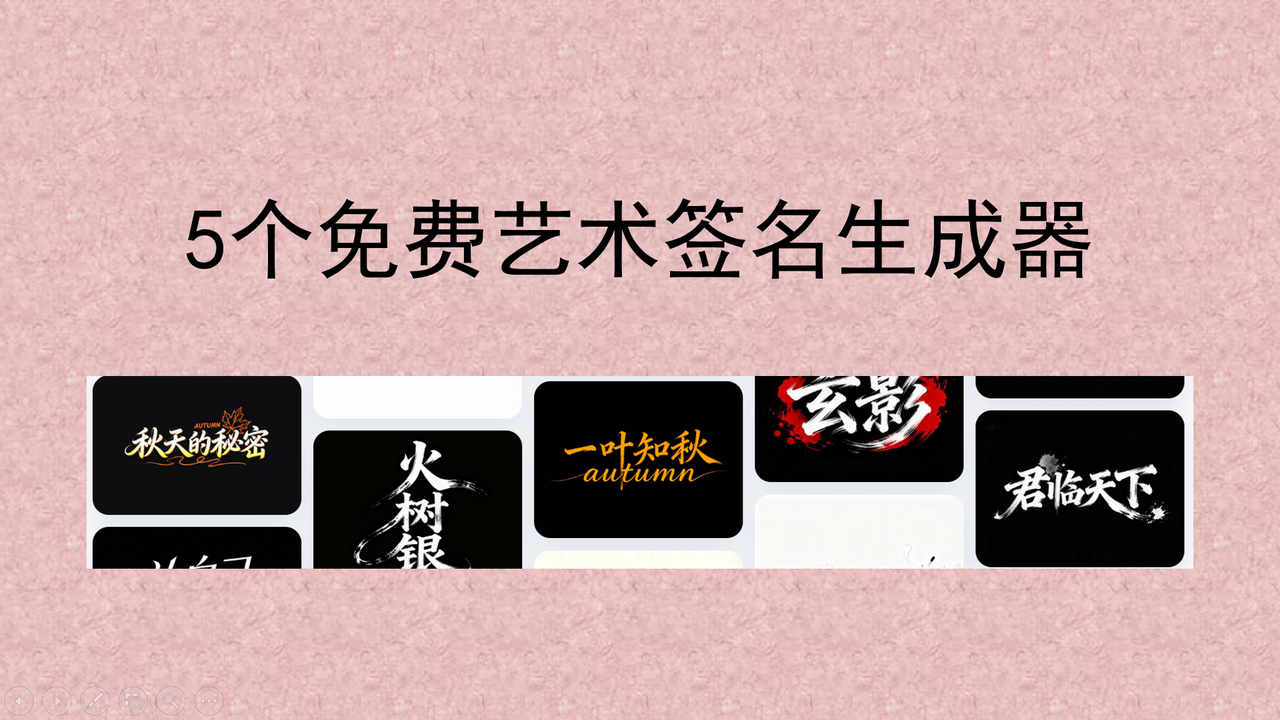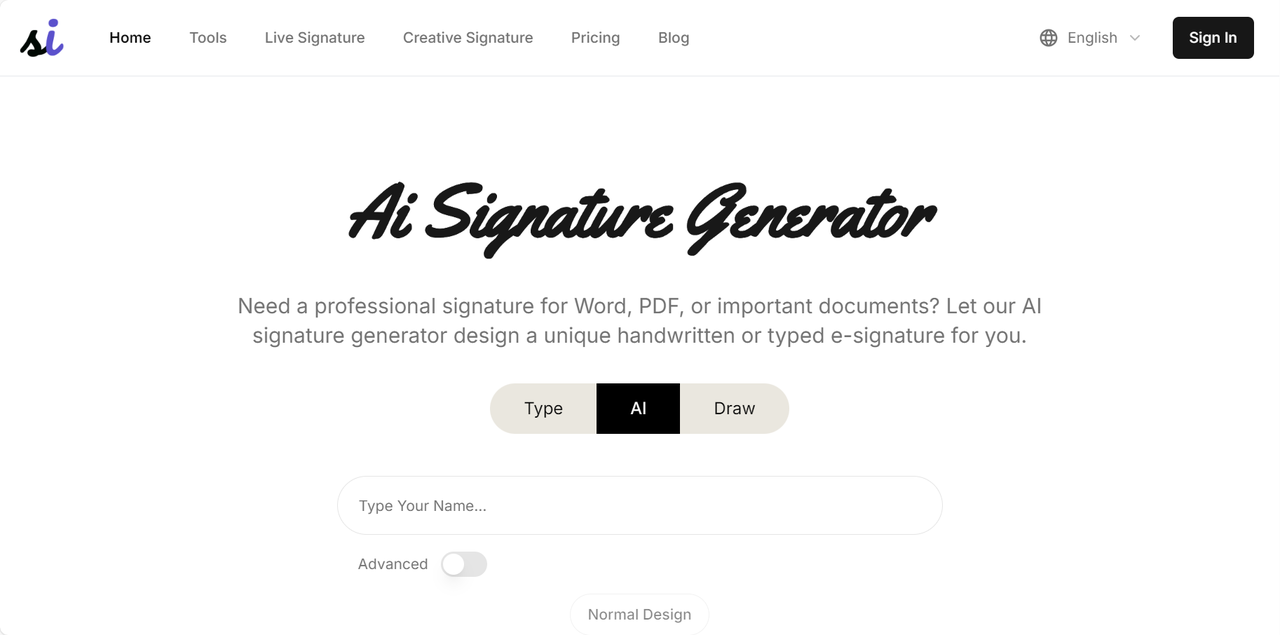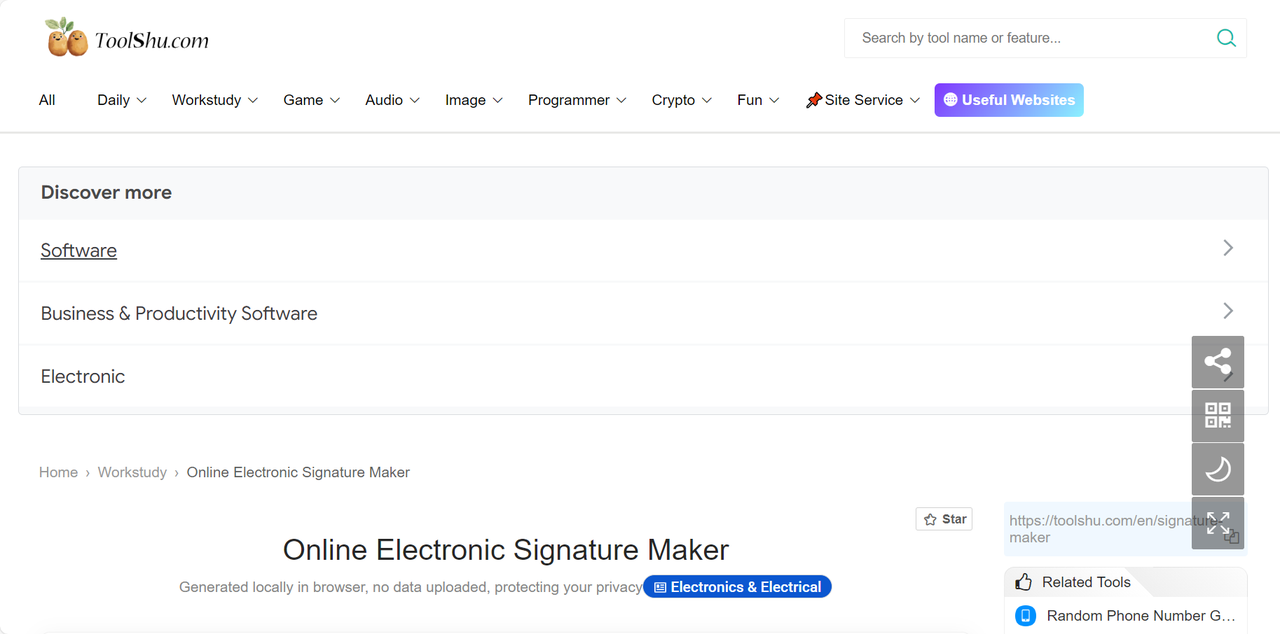
不用找设计师!免费艺术签名在线生成,3 秒出效果
很多人手写签名练的很好,但是一到电子签名时就歪歪扭扭,控制不好鼠标,连自己看了签名都觉得不够体面。一个与众不同的艺术签名,不仅能够彰显个人品位,更是个人品牌形象的重要组成部分。在当今科技飞速发展的时代,大家完全不必再为设计签名而苦恼,很多免费的艺术签名在线生成工具都能快速设计签名,短短几秒就能获得一款高颜值手写风艺术签名!生成后的签名还可以直接保存为透明背景的图片,不管是电子合同、简历、PPT、邮件还是其他场景,都可以直接一键应用。接下来就给大家介绍 5 个亲测好用的艺术签名生成工具,彻底告别“手残党”的尴尬!
一、字由
字由是国内设计师最常用也最方便的一款字体工具,目前已有超过 2000 万用户注册使用,提供500+品质正版字体商用授权,并提供 AI 识字、字体特效等实用设计工具,是设计师必备的字体管理神器。除此之外,在帮助普通人打造艺术签名这个领域,字由也是一个绝佳助手,最简单便捷的方式就是利用它的 AI 字体功能。打开字由官网,在上方菜单栏点击【字体工具】——【AI 字体】,进入后可以看到上百种 AI 模板,包含多种字体风格;我们在分类筛选区域点击“个性签名”,找到自己喜欢的艺术签名效果,在文本框输入你的名字,等待 30s 就可以得到一张同款艺术字签名。输入的文本字数最好和模板样图的字数一致哈,这样字体生成效果会比较准确,也更容易符合你的预期。这里建议大家下载的时候选择透明背景的 PNG 图片格式,这样便于后续直接使用。
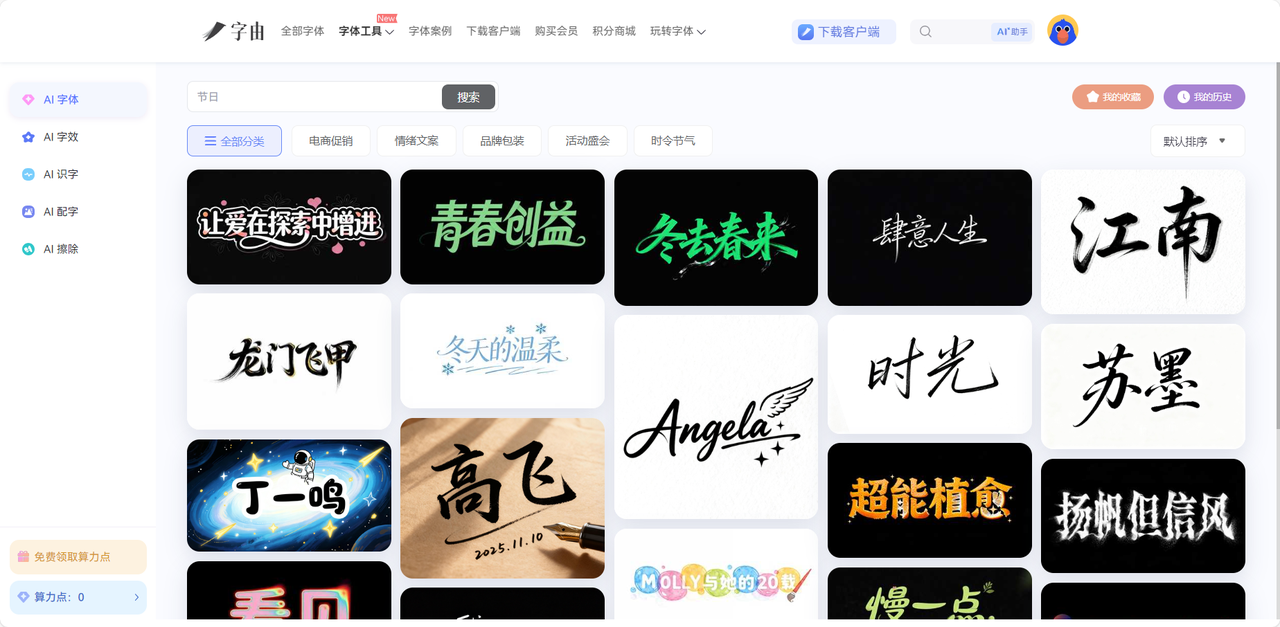
二、SignatureGen.ai
SignatureGen.ai 是一款 AI 驱动的在线签名生成工具,只需要输入你的名字,系统就会自动生成多种风格的艺术字签名供你选择。它提供了三种生成艺术签名的方式:常规字体签名、AI 生成签名和手写模拟签名。我最常用的还是 AI 生成签名,这也是 SignatureGen.ai 最大的特色,你可以额外向它描述想要生成的字体风格倾向,给它提要求,要求越详细越容易生成你满意的签名效果,而且它的笔触还是比较真实的。如果你偏向于更华丽的签名设计,SignatureGen.ai 还有一个创意签名的功能,可以将签名和简单的简笔画元素融合到一起,比如会在某些笔画边缘嵌入一朵小花、一颗星星、一片叶子等极简的图标,可以让你的签名更具辨识度。
三、Toolshu Electronic Signature Maker
对于非常注重隐私和数据安全的用户而言,Toolshu Electronic Signature Maker 堪称最理想的选择,它是一款可以完全在浏览器本地运行的电子签名生成工具,所有操作都是在本地完成的,自己的名字也不会被上传到网络服务器。说起艺术字签名,用户想要体验更高自由度的设计过程可以选择它的手绘模式签名设计,也就是说直接用鼠标、触控板或者手写笔在绘图板上书写签名。它会根据书写速度自动调节线条的粗细变化,模拟真实手写字体的笔墨变化,更加真实自然随性。不过这个功能也比较考验用户自身的书写能力,不适合新手小白哦。觉得自己的手写效果不够好看,还可以选择 Toolshu Electronic Signature Maker 字体生成模式。你只需要挑选一款自己满意的书法字体风格,输入自己的姓名,点击生成就可以获得同款字体的签名了。
四、Refont AI
提起 Refont AI,大家应该也比较熟悉了,它是一款兼具艺术性与个性化的手写签名生成工具,输入姓名后,可以快速将其转化为手写体或是各种书法风格的签名。Refont AI 最大的特色在于它对书法美学 的专注研究,毫不夸张地说,用它生成的签名都会带有真实的笔墨过度、笔锋变化和连笔走向,从视觉上更加接近在真实纸张上的书法作品,所以经常被用于品牌签名设计、婚庆邀请函设计、艺术作品创作等领域。最值得一提的是,Refont AI 还会根据姓名结构来进行布局优化,比如你是三个字的名字,它会在生成签名的过程中自动调整字体的重心和间距,给人最完美的阅读体验,确保整体造型更加美观均衡。
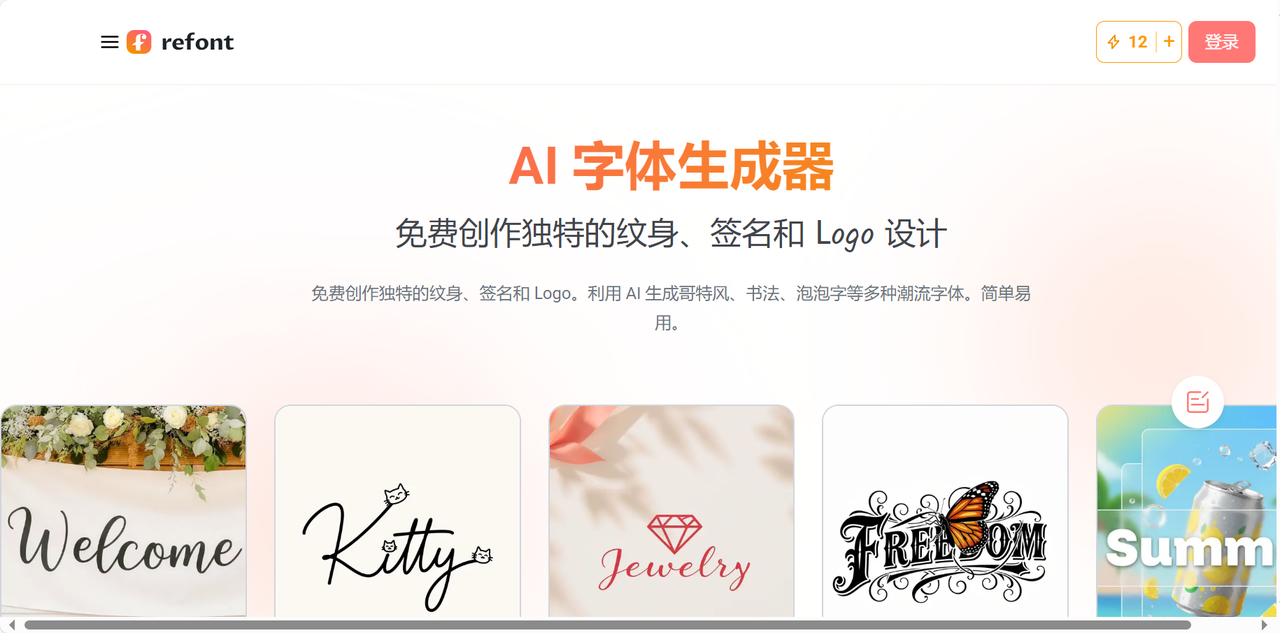
五、OnlineToolkit Cursive Signature Make
最后要给大家推荐的艺术签名在线生成工具就是 OnlineToolkit Cursive Signature Make,它主打连笔草书签名效果,极简的操作界面和丰富的自定义选项也让它深受用户的青睐。这款工具最擅长生成行云流水般的连笔字签名效果,非常适合用来生成生成笔画较多的英文名字!我要强烈推荐 OnlineToolkit Cursive Signature Make 自定义调整面板,你可以在字体生成后,再独立调整签名的尺寸、颜色、字体样式或者是笔触质感。这也就意味着,哪怕 AI 生成的签名效果比较相似,但是通过后续的自主调整细节也可以呈现出完全不同的视觉效果,打造独一无二的签名。和 Toolshu 类似,它同样也支持手绘签名,即使用鼠标操控也会自动生成相对流畅的笔画线条,至少让字体看起来不那么生硬。
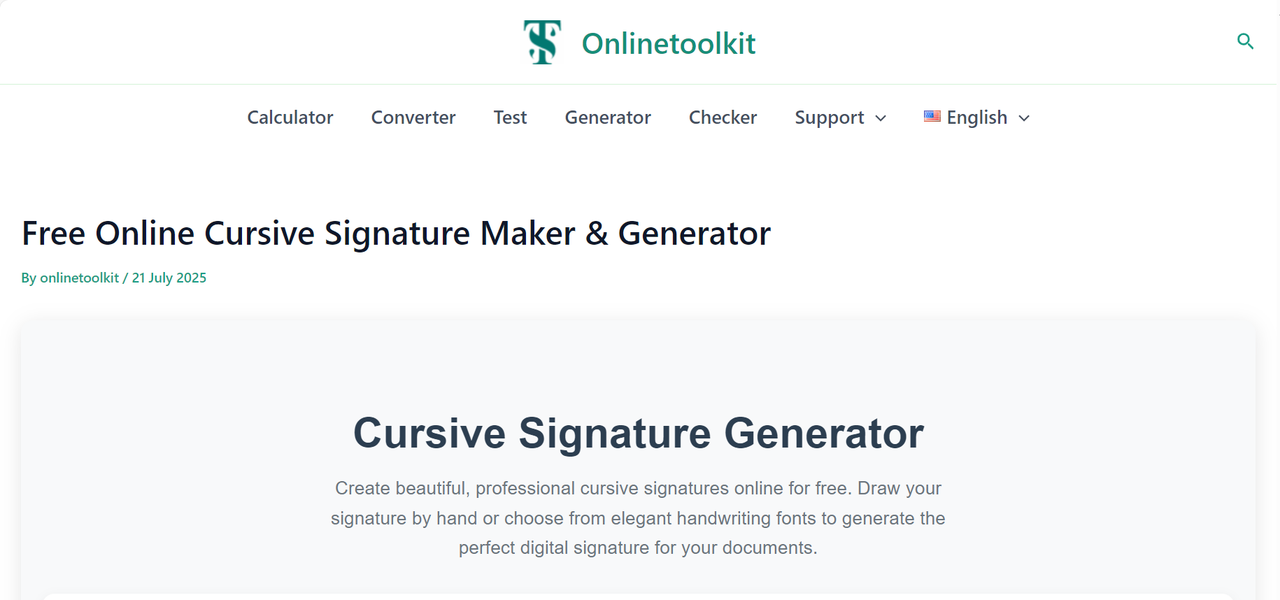
总的来说,上面的这 5 款免费艺术签名在线生成工具都是非常好用的,从 AI 自动生成到手绘自由创作签名,从国内的全方位一站式字体管理工具到国外工具的绚丽字体,满足了不同偏好、不同使用场景、不同用户的全部需求。你如果只是想要生成一个日常使用的签名,本文的哪个工具都可以实现,如果你对签名设计还有更高的要求,可以多去尝试体验一下不同工具的魅力,毕竟它们擅长的生成模式各不相同。相信有了这些工具的帮助,想要拿出一款拿得出手的艺术签名也会变得非常容易!